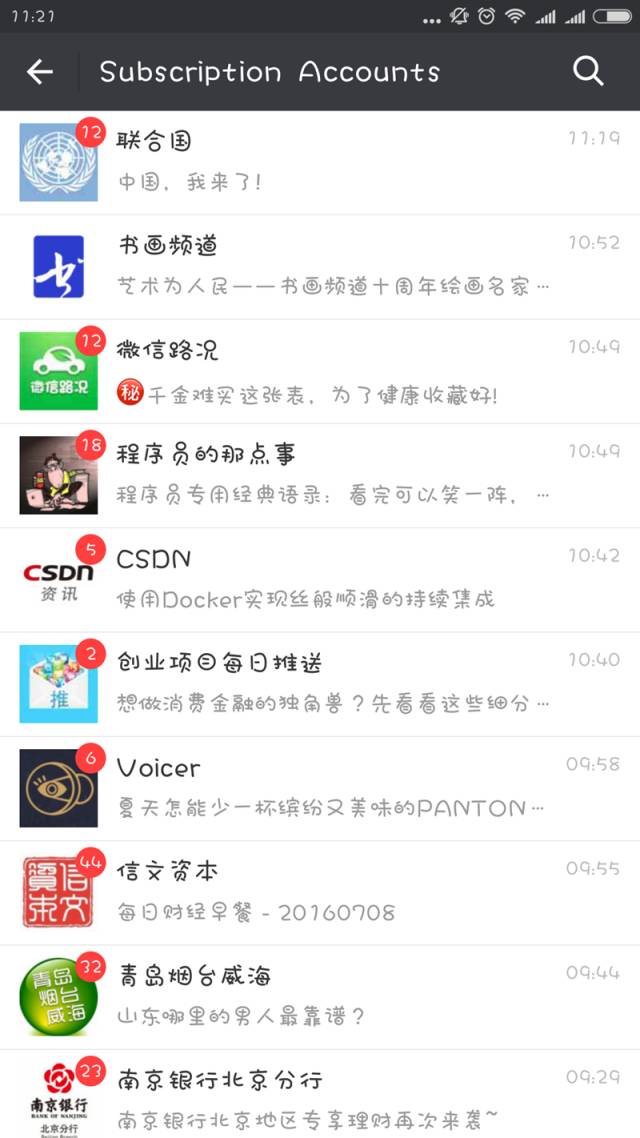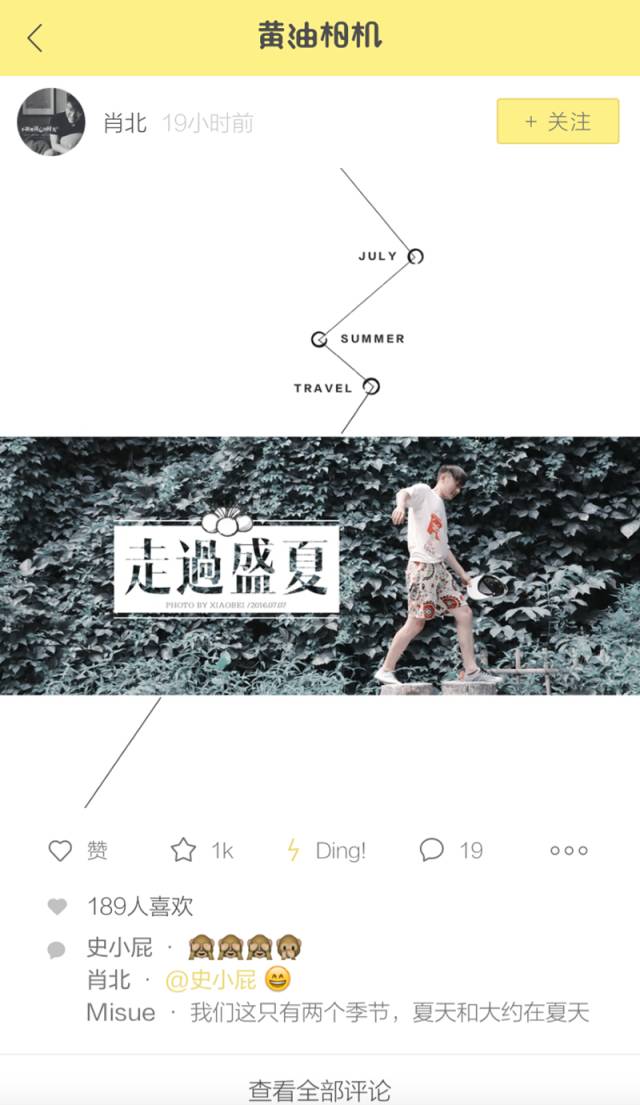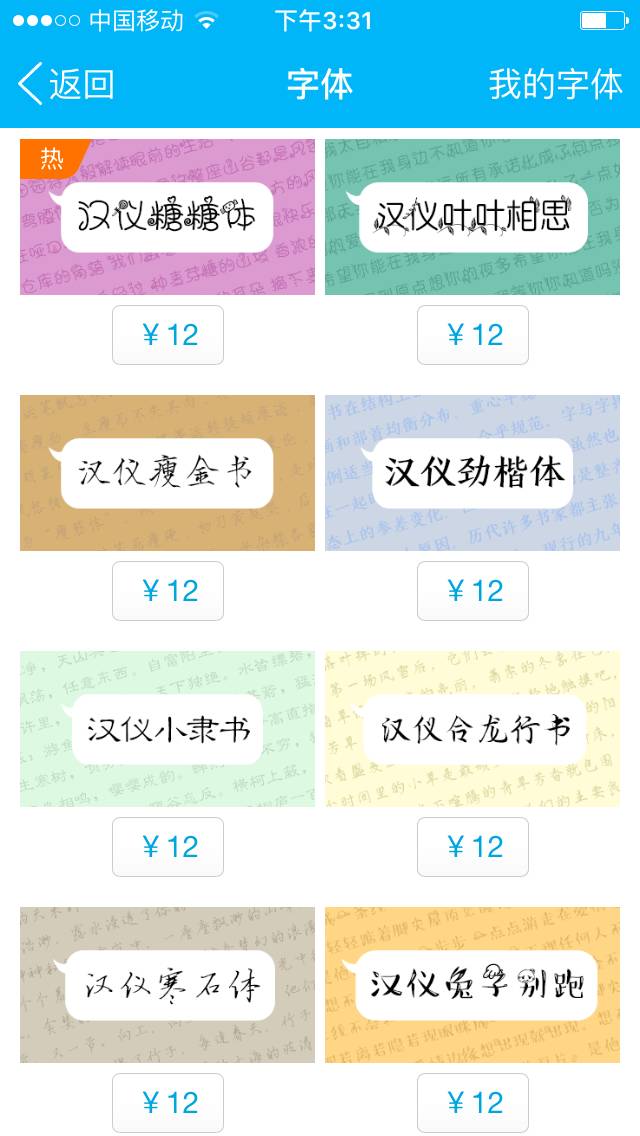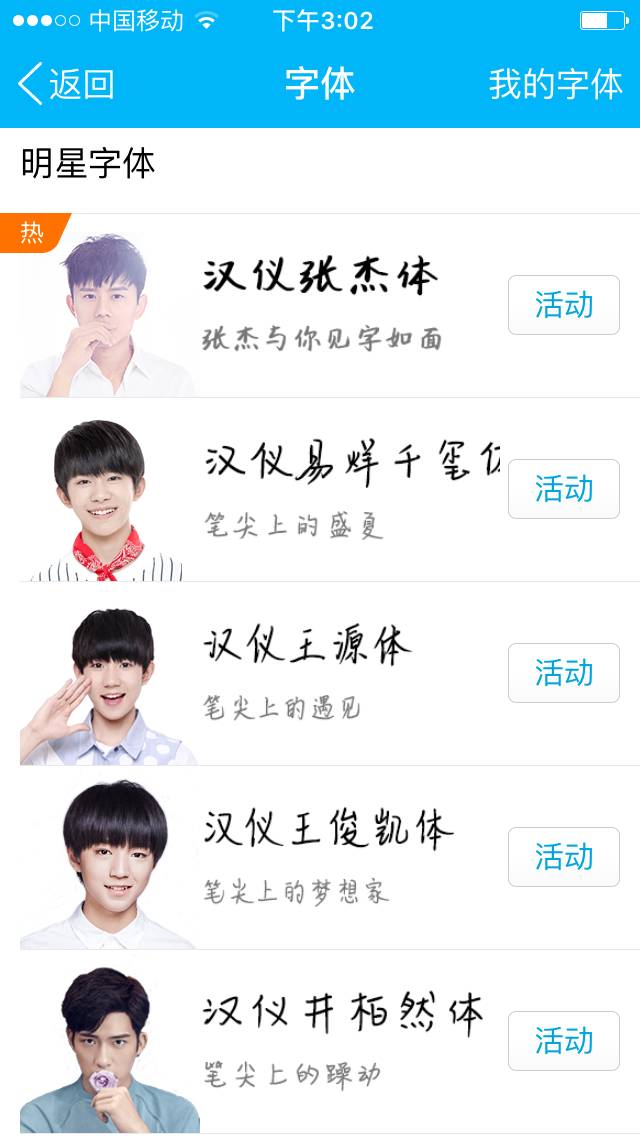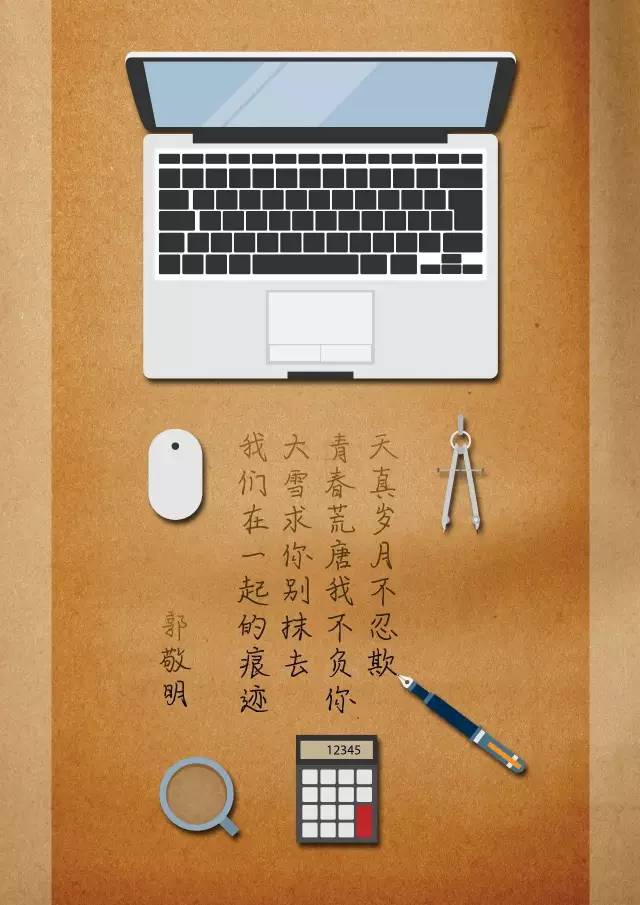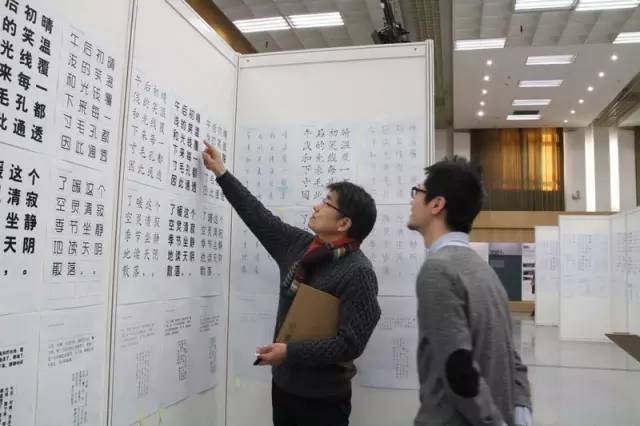
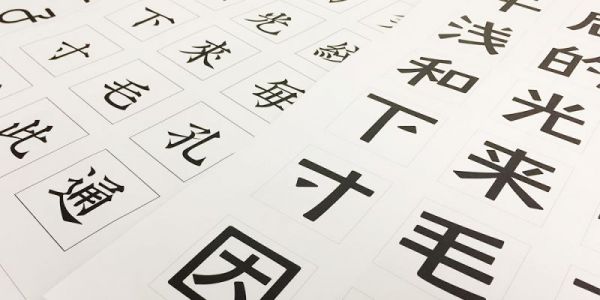
移动互联网时代,谁说字体设计没饭吃?
编者按:北京汉仪科印信息技术有限公司(以下简称“汉仪字库”)成立于1993年,是中国大陆最早专业从事字形设计、字库产品开发、汉字信息技术研究、汉字应用解决方案的文化创意与信息技术企业。近几年,通过转变思维,介入移动互联网思维领域,汉仪字库逐渐探索出新的商业模式。字体的应用,也从传统的印刷、出版、设计等专业领域拓展到大众领域。目前,仅腾讯QQ一项,就让汉仪拥有了3.4亿的用户群体。近期,本刊对汉仪字库的CEO谢立群进行了专访,对汉仪字库在移动互联网时代的探索进行了解读。
字体公司的新探索
在人人都是低头族的时代,似乎生活的方方面面都可以集中在方寸之间的手机屏幕之上。但对于传统的字库公司来说,让字体与移动互联网联姻,从意识和实操层面来讲,都并非易事。
传统的字库公司面向印刷、出版、设计等相关行业的从业者,经营的模式从最早的出售字库光盘到之后的字体授权,生意并不好做。侵权行为的泛滥令字库公司不得不全副武装,搭建维权团队,以维权模式作为生存路径。维权的路不好走,同时,在谢立群的眼中也不是一个公司应该有的正常的商业模式,它不仅耗费人力、物力、财力,与客户之间剑拔弩张的关系也不利于树立良好的公司形象。他一直在思考如何通过正面的方式来推进业务的发展,能不能依靠互联网让字库公司找到轻便型的商业模式。
2012年是移动互联网的爆发年,借助当时蓬勃发展的趋势,汉仪开始和搜狗输入法开展合作。双方尝试的是一些个性化的内容,比如浮动窗口的字体以及皮肤。小试牛刀之后,汉仪与360合作开发了手机桌面。这方面汉仪是国内第一家涉足此领域的字库公司,当时业内还没有人想到可以把文字应用到这些平台上。通过设置字体,用户手机桌面上的图标文字可以切换为自己喜欢的字体,满足个性化的需求。正如360手机桌面字体对产品介绍中所写的:“文字本身就是一种图形,它不仅是一种交际的工具,更是一种美的载体,是一种视觉审美对象……”与360合作的初期,汉仪提供了九套免费的字体,颇受手机用户的青睐,短短的时间下载量就达到了三千多万。这样的用户反馈让汉仪“脑洞”大开,意识到了潜在的机会。
“以前的字体作为一种设计元素主要是设计师在用,它直接接触的人群是设计师群体,与读者的接触需要经过设计师这个中间环节,而且主要的应用领域是传统的出版印刷行业。没有人想过文字在大众领域也会十分受欢迎。这说明美的东西、有艺术价值的东西,或者好玩的、贴合用户心理的、年轻人喜欢的东西就会受到市场的欢迎。”谢立群这样解释字体应用的大众化。
从360手机桌面开始,汉仪将商业触角伸向国内的手机终端领域。现在国内使用安卓系统的主流手机厂商几乎都成为汉仪的合作伙伴,比如华为、小米、酷派、OPPO等等。一方面,由于现在的手机厂商自己控制root权限,以前做桌面的公司不能读取到桌面内的信息,业务就慢慢萎缩,导致这方面的业务逐渐转移到手机厂商那里;另一方面,各个品牌手机的应用商城、主题商城的产品灵活度和丰富性大大增强,为字体的个性化应用提供了空间。比如在小米商店的主题类产品中,“字体”这个类别下就提供七百余种选择,其中包括汉仪的六十余种字体。2014年,汉仪的“乐喵体”还获得了小米主题商城的年度最佳字体。另外,汉仪的字体也逐步在各类APP上得到应用。也许作为用户的你并没有意识到,但是诸如“网易新闻”“美丽说”“黄油相机”等受众广泛的手机应用程序中,都在使用汉仪的字体。
汉仪乐喵体在小米手机上的应用
汉仪瑞意宋在黄油相机App中的应用
打通了字体在手机终端使用的路径以后,汉仪并没有就此止步。手机桌面上的应用,针对的只是用户自有设备的个性化设置,只有用户自己可以看到,并不能与其他人分享。接下来,汉仪想探索的是,能不能通过某种方式让这样的个性化字体成为用户之间可以互相看得到的、共享的内容,让用户的“个性”得到有效的展示,满足他们的心理需求。
由此,汉仪想到了国内最普及的网络即时通讯软件——腾讯QQ。与腾讯的讨论,最初的想法是通过云端字库的方式实现个性化字体的使用和显示。通常使用的TureType字体大小一般有几兆甚至十几兆,如果在网络聊天中使用,以用户之间网络传输的方式实现并不现实。双方想到了云端的解决方式。云端字库是通过把字体提成子集,放到云端,在用户使用时再抽取,以此来节省字体的存储和传输空间。一套字库通常有六千多个字的国标字体,而用户在聊天时使用的十几个字,可以从云端实时抽取。但经过分析,这个办法的可行性也受到了质疑。因为腾讯的用户是亿级的,他们在聊天时对字体的使用频率太高,从云端抽取数据太频繁,服务器根本无法支撑。在放弃这个想法以后,汉仪注意到上海驿创信息技术有限公司的FullType全息曲线轮廓字形技术和基于该技术的“电脑书法家字模创作系统”,通过此项技术,一套汉字可以被压缩到300Kb,这样的文件大小对于现有的网络环境来说已经毫无压力,与腾讯合作遇到的技术核心问题迎刃而解。2013年,汉仪全资收购了上海驿创,将其纳入麾下。有了技术的支持,又经过大量的测试工作,汉仪与腾讯实现了字体在聊天工具中的使用,在社交软件中实现字体的使用与共享这一模式也因此建立了。
除了在QQ聊天中应用小字库技术,在QQ空间、QQ音乐以及其他的聊天室中的用字,都可以用FullType小字库技术实现。现在其他的字库公司也在逐步开展同类的业务。谢立群认为,这是技术发展到一定程度的必然结果。目前,汉仪为QQ提供了两套免费的字体——汉仪蝶语体和汉仪南宫体供用户使用,其他字体收费,每款售价12元。上线后不久,仅安卓版手机QQ每天付费的用户就超过一万。2015年5月,苹果版手机QQ的群聊也上线了,汉仪字体每天的付费用户达到了两万多,收益大幅增加。在2016年3月举办的北京汉仪字库第二届“字体之星”大赛颁奖典礼暨2016新品发布会上,汉仪专门邀请到了腾讯SNG社交网络事业群增值产品总经理刘宪凯到会,足见汉仪对双方合作的重视。
汉仪的移动互联网业务发展以来,营业额从以前的百万元级别跨越到千万元。在2015年的数据中,来自移动互联网的收入已经占到总收入的一半。截至本刊采访时,2016年公司来自移动互联网的收入已经占到总收入的三分之二以上。谢立群预测将来这个比例会进一步提高。
字体应用的大众化
从设计层面来讲,面向传统出版印刷行业与面向大众的字体设计有着不同的方向与要求。为了迎合大众的口味,汉仪专门组建了针对移动互联网的团队,研究年轻人的字体偏好。目前推出的字体,整体上的特点是个性化,而可爱的、卡通的、带有装饰的字体都是比较受欢迎的类别。汉仪糖糖体的部分笔画变形成为棒棒糖一样的螺旋状、蝴蝶结,或者丝带的样子。手机QQ上对其特点的描述是“口中的甜蜜,慢慢到心里”;汉仪猴海森体则在较为卡通的字体基础上加入了动作各异的小猴子剪影,让用户“猴年天天猴嗨森”。还有部分书法体也颇受用户的喜爱,比如汉仪寒石体,是一款行书字体,“既有楷书的端庄、稳重,又不乏草书的飘逸洒脱”。
手机QQ 中的汉仪字体
手机QQ 中的汉仪明星字体
为了吸引腾讯QQ上以“00后”为主的用户群体,汉仪自2015年开始在手机移动端推出了明星字体。对于明星的选择,需要满足一些条件。他们不仅需要具备在青少年群体中足够的人气,字也要写得不错,同时自己也要有这方面的意愿。明星字体开发的过程是:先由明星手书约八百个常用字,之后汉仪需要根据他的笔形风格特点人工拼全整个字库的近七千个字。明星手写的时间大约耗时两周,后期完成则需要一个月左右。
郭敬明是汉仪选择的第一个明星。他不仅仅身兼作家、导演、杂志主编等角色,也是颇受争议的公众人物。恰恰是他身上持续存在的争议与关注度,令这款汉仪郭敬明体在上线短短几个月时间就为手机QQ带来了非常可观的收入,且长尾效益还在持续发挥作用。接下来,汉仪陆续推出了井柏然体,TFBoys成员易烊千玺、王源、王俊凯的手写字体,以及刚刚上线的张杰体。在推出TFBoys成员手写字体时,汉仪也曾经有过顾虑。一方面,这几个少年“字的水平一般,就是十几岁普通孩子的水平”;另一方面,对于在这三款字体前加上“汉仪”这两字的影响,也让公司一些成员有些担忧,恐怕影响了汉仪这个品牌。在反复考量之后,汉仪还是决定做下去,因为他们对于自己的字库产品具有足够的信心。面向大众的明星字体只是他们产品家族中的一部分,除此以外,专业的正文字体、标题字体、书法体等完全可以体现汉仪的专业水准。事实证明,这三款字体带来的效益不仅体现在收入和扩大品牌影响方面,更有趣的是,它们激发了很多青少年好好练字的欲望。谢立群十分认可这种积极的影响——“这就是偶像的力量”。
汉仪郭敬明体
目前,汉仪的产品在手机QQ上的用户群体有3.4亿。他们的平均年龄是14岁,60%的用户年龄集中在13-16岁。他们对于明星体的喜爱在数据上也有所体现,汉仪在明星体方面的收益已经占到全部手机QQ产品的一半。对于大众化的审美取向会不会影响字体设计的专业性,或者导致其幼稚化的问题,谢立群的看法是比较乐观的,“字体大众化对字体设计的影响是积极的,它让设计更加多元化,更加丰富。即便幼稚也OK啊,任何东西都有它存在的理由。只要它是正向的、积极的”。在采访中,谢立群还透露,目前汉仪正在研发针对手机QQ的彩色字。“我们给汉字加了另外一个维度。不是简单地给字体设置一种颜色,而是将每一个字都进行设计、定义”。依照他展示的样例来看,彩色字有些是将字库中某一些汉字做彩色处理,有些则是在特定笔画上下功夫,或者加上彩色的装饰。这也是针对年轻人的喜好开发的产品,预计将在今年8月份上线。
井柏然在创作中
汉仪在字体大众化方面的尝试不止于此,未来他们还计划推出属于用户的个人手写字体,谢立群称其为“字体的UGC(User Generated Content,用户原创内容)产业”。“现在做手写字体的技术需要先写出几百个字,甚至要写出所有的字,才能完成一套字库。这对于一般用户来讲是一件很苦的事情,而且字库公司也没有那么多精力帮用户完成这件事情。我们希望未来用户只需要写几十个字,就能生成一套字库出来”。这是汉仪希望实现的目标,其技术团队也正在为此努力。相信不久的将来,拥有一套属于自己的手写字体,将不再是难事。目前,汉仪B2C部分的业务已经摸索出一条自己的路径,而对B2B的业务还在进一步探索。谢立群坚定地说:“目前字体的企业用户不多,这条路不太好走。但是我们愿意付出一定的代价去探索,即便短时间影响到公司的营收也会去尝试。”
轻资产、半创业
作为中国最早的字库公司,汉仪近些年经历过不少波折。汉仪创办之初是由中国印刷科学技术研究所(简称中印所)与台湾台泥资讯股份有限公司(简称台泥)成立的合资公司,在中国大陆曾经是市场上最大的中文字库供应商。2000年前后,因为侵权行为严重,印刷出版行业萎缩,包括汉仪在内的字库公司遭到了前所未有的冲击。2005至2009年,“公司一直在赔钱”,改变势在必行。因为利润太薄,台泥曾经的董事长辜振甫的后人不愿再继续这个领域的业务,遂在2009年撤资。中国印刷科学技术研究所所长、现在汉仪字库的董事长陈彦主持将台泥的股份收回,汉仪变为国有企业。此后,汉仪进行了股份制改革,一方面实施员工持股计划,另一方面寻找投资方,对接资本市场。目前的汉仪是股权多元化的企业,国有资产部分占35%,员工占40%,另外一些为投资方占股。
通过MBO(管理者收购)的模式,汉仪一半以上的员工成为公司的股东。当然,由于经历波折,公司员工曾经出现断层,不少老员工在业务出现问题时相继离开。目前公司的员工绝大多数都是2011年以后加入的,很多骨干来公司的时间不过三五年而已。股权激励的做法,不仅唤起了员工的信心,还激发出他们的积极性与创造力。目前北京的汉仪字库和上海的驿创共有员工八十余人,设计师占一半以上,然后是市场、销售、技术人员以及行政支持等。谢立群将持股员工的工作状态称为“半创业”。“他们的自驱力非常强。虽然比普通的上班族多付出一些心血,多思考一些,但不一定要多辛苦。一个好的点子比加十天班更有价值”。目前,汉仪在工作时间上也给员工一些弹性,以照顾以设计师为主的员工晚睡晚起的作息习惯。
移动互联网改变着我们的生活方式,也对设计相关的人、事、物提出了新的挑战。汉仪的探索让我们看到了传统的设计行业在新时代、新的背景下生发出的新鲜活力,以及创造性思维发挥的作用。同时,汉仪对商业道路的选择不仅仅是以利益为导向的,它仍然坚持产品的专业性和多元化。目前,判断字体大众化对于设计、文化的影响究竟如何还为时尚早,但如果禁锢在传统的牢笼之中,无疑会将这个行业引向衰亡。对于传统的设计行业来说,汉仪的案例提供了颇为难得的启示。